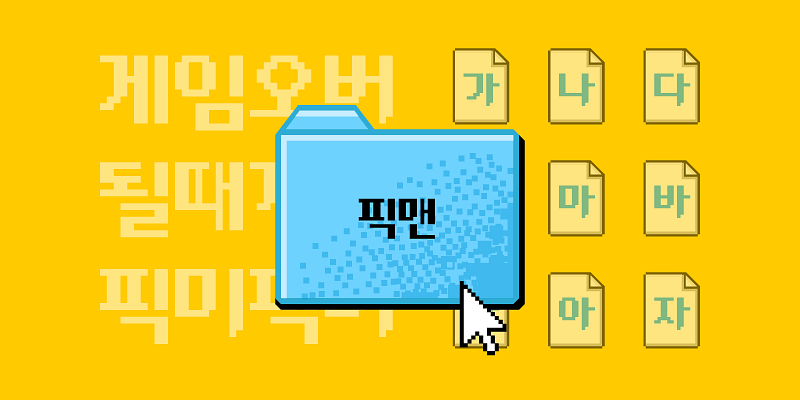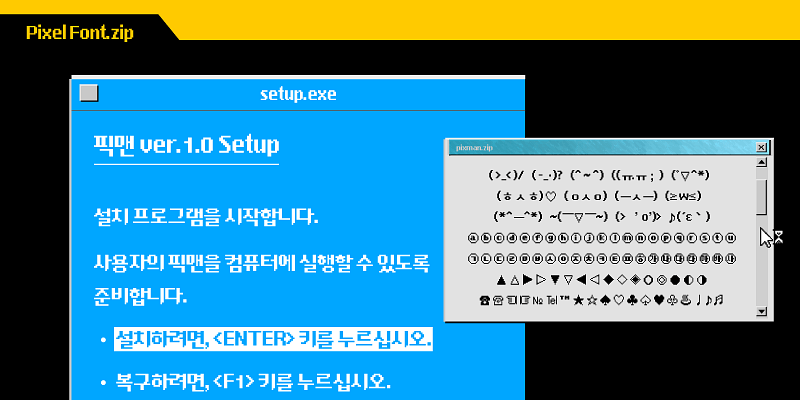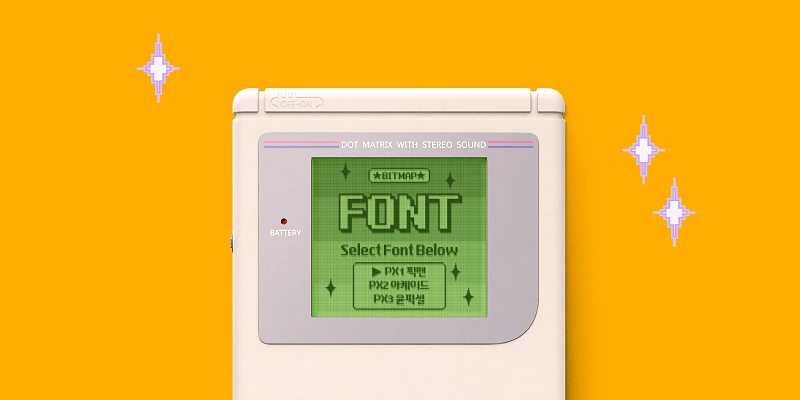
Dies ist eine Pixelschrift der Yoondesign Group, die traditionelle Pixelschriften vergangener Tage modernisiert und vektorisiert, um sie an zeitgenössische ästhetische Empfindungen anzupassen.
Die verspielte und fröhliche Atmosphäre der Schrift wird durch die wenig modulare Form verstärkt, während die deutlichen schrägen vertikalen Striche ihr einen faszinierenden letzten Schliff verleihen. Dank der Unterstützung von 11.172 Hangul-Zeichen gewährleistet sie eine umfassende Darstellung aller koreanischen Buchstaben.